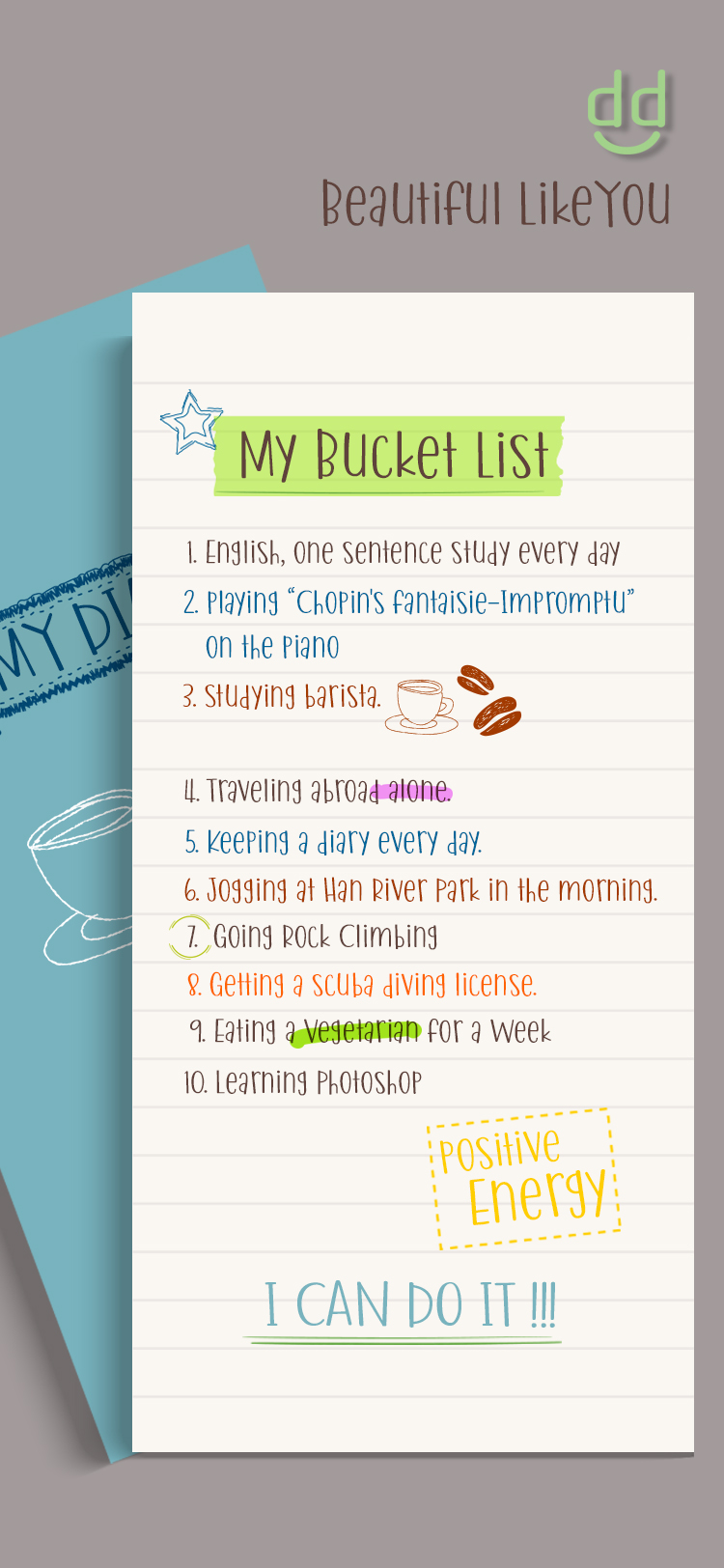
DDBeautifulLikeYou Dd Font 사용예시 크게보기 소문자의 높낮이가 균일하게 구성되어 독특한 매력이 느껴집니다.모던함과 엔틱함이 공존하는 서체입니다. 종수 1종 출시년도 2023 스펙 라틴 95자 / 숫자 10자 / 부호 991자 포맷 TTF 파일명 DDBeautifulLikeYou 지원언어 영어,기타 지원프로그램 일러스트, 포토샵, 피그마 등 프로그램 지원 태그 상품 정보 더보기 리뷰 () 리뷰작성 함께 쓰면 좋은 추천 폰트 채희준 4종 고요 디나모 20종 ABC Whyte Inktrap 한글씨 6종 HG아몬드 해피뉴타입 1종 HNT 샤프고딕 요즘 인기 콘텐츠 1 북마크 필수! 감 좋은 레퍼런스 사이트 디자인 트렌드 2 0원으로 대학생활 걱정 끝! 캔캠 시즌8 산돌구름 3 2026년 K-POP 앨범 속 폰트 찾기 디자인 트렌드 4 여신의 손글씨를 탐한 「뮤즈」 비하인드 5 무한한 생성의 바다에서 결정적 한 컷을 포착하는 감각 피플 인기 콘텐츠 더보기 이 폰트와 유사한 유료 폰트AI검색 게아폰트 GHEA Dvin 14종 해당 폰트는 현재 산돌구름에서 제공되지 않습니다.